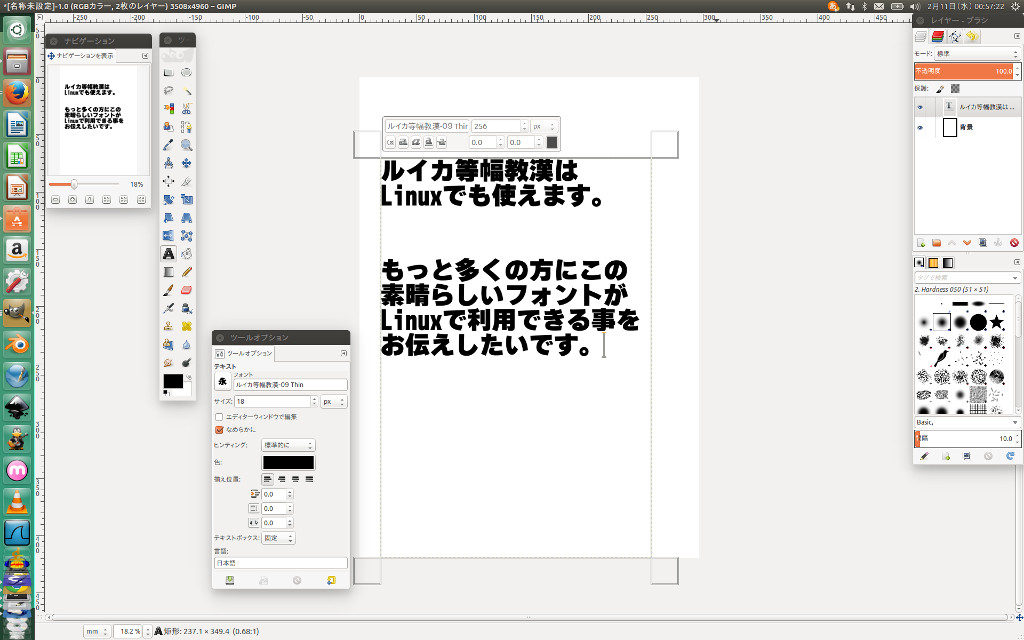
お忙しい中恐縮ですが、お返事いただければ嬉しく思います。
さとうゆたか  2016年5月16日(月) 7:38 [修正]
はるおさん、お問い合わせありがとうございます。
通常の商用利用(印刷物や看板〜)だと思いますので、何の問題もありません。
がんばって販売していただければ…、と思います。
・スヘるお  2016年5月16日(月) 23:24  Mail [修正]
佐藤さま
早々にお答えいただきましてありがとうございます!
それでは有難く利用させて頂き、
がんばって販売していきたいとおもいます。
ありがとうございますm(_ _)m
大学の卒業研究で  ねぎま  2016年2月20日(土) 15:55
こんにちは。
フリーフォントを探しているなかで、こちらの無料配布のフォントのいくつかに心惹かれました。
当方は卒業研究に勤しんでいる大学生なのですが、その卒業研究でフォントに関する調査をしようと思っているのです。
そこで、こちらの無料配布のフォントを研究の材料(ポスターに入れる文字フォント)として利用させていただくことは可能でしょうか?実験内容としては、ポスターに描かれたフォントに関する印象評価、のようなものになります。
私の調べ不足でどこかにこの旨に関する記載がありましたら申し訳ありません。
どうぞよろしくお願いします。
さとうゆたか  2016年2月20日(土) 16:48 [修正]
よくある質問のページに記してあるように、仕事に使っても構わないのですから、研究の材料に使う程度のことに制限をつける気持ちはありません。
どうぞ、利用してください。
ねぎま  2016年2月20日(土) 18:21 [修正]
お早い回答、誠にありがとう御座います。
有り難く利用させていただきます。
タイプラボさんのフォントは冗談抜きで凄い!  くろろ〜ん  2015年10月19日(月) 21:54  Mail
こんばんは!
自分は動画制作をしています。
とは言っても、ずぶの素人で投稿すら至ってませんが(汗
前回に購入した、タイプラボさんのルイカ、わんぱく、ハッピー、アニトなど他にもありますが、とても好きになりました。
特にルイカフォントを動画画面に字幕を付けるだけで、凄まじい位にパワフルな存在感でした。なるほど、だからテレビ番組のテロップでも使われるのかと自分で納得しました。
今現在も、その画面を見るだけで、気持ちを奮い立たせられ『次も頑張るぞ!』と前向きに取り組む様になりました。
文字サンプルでは『ハッキリしていて良い』、『文字が綺麗』と思いましたが、実際に使用して、改めて文字の力というものを実感しました。
以上、長文で駄文になってしまいましたが…。
これからも、フォントをフリーで提供して下さるその善意に、感謝の念を絶やさず、また他のフォント素材屋のサイトさんも同じく、これらのフォントを大切にしてゆきたいと思います。
さとうゆたか  2015年10月20日(火) 14:57 [修正]
熱い感想を投稿していただき、ありがとうございます。
使うフォントによって、モノのイメージって大きく変わりますよね。
そこに気づいてくれてウレシイです。
これからも、フォントをうまく使いこなしてください〜。
WEBフォントとして使用する場合。。  近藤  2015年4月15日(水) 13:50  Mail
いつも使わせて頂いております。ニタラゴルイカはじめルイカは素晴らしいです。
弊社は複数のアーティストサイトをやっていますが、ルイカなどを弊社サーバーにおいて
WEBフォントとして使用する際、どういった費用感、契約になりますでしょうか?
よろしくお願いします。
さとうゆたか  2015年4月15日(水) 14:00 [修正]
よくある質問(Q&A)ページに記してある通り「デコもじ」というWEBフォントサービスを利用してください。
デコもじ↓
↑費用なども詳しく説明されていますので、よろしく〜。
追記…  さとうゆたか  2015年7月28日(火) 21:59 [修正]
フォント組込み契約の対象物件に、WEBサーバを追加しました。
●以下のフォント組込み使用許諾契約書をご覧ください
・総合書体の場合
・かな書体の場合
画像の中にフォントを使用して、その画像を投稿してもいいんですかね  しゅんY12  2015年7月8日(水) 22:53  HP
はじめまして、
先日タイプラボさんの無料版フォント(ニタラゴルイカとキャパニト)をダウンロードさせていただいた者です。
題でも述べましたが、自分のブログやツイッターなどに、『画像のテロップ」の中に、
そのフォントを使いつつ投稿するのは違反行為ですか。それとも普通に使っていいですか。
注意点を読んだんですが、これは「改変」とかにはあたりませんよね?
著作権的な意味でやや心配しておりまして。
心配しすぎ…  さとうゆたか  2015年7月9日(木) 8:35 [修正]
以下のページを読んでいただけたんですよね。
「テロップなどに文字を画像化(アウトライン化含む)して使う分には、上の問いの答えのように自由に使って構いません」と記してあります。
心配しすぎですよ(笑)。
ま、フォントを配布しているのに、いざ使おうとすると制約が多すぎて、実際には使用できそうもないフォントや制約を強いるフォント作者がいるようですが…。
ダウンロードURLの書いたメールが届きません  ももは  2015年7月1日(水) 14:18
つい一月ほど前、無料配布フォントを使用したくメールアドレスを記入したメールをそちらにお送りしたと思うのですが、ダウンロードURLが記入されているはずのメールは届かずメルマガだけが今日届きました。
メアド間違い、というわけではなさそうなのでどうなっているのか…知りたいところです。
また改めて申し込みをすべきなのか、対処方法が分からず困っています。
ちなみに『ルイカ』をDLしたくその時に申し込み手続きをしました。
ご面倒かとは思いますが、回答の方よろしくお願いいたします。
さとうゆたか  2015年7月1日(水) 14:30 [修正]
まずは、無料配布フォントの登録後に表示される以下のページを読んでください。
上記の内容に該当していないのに、メールが届いていない場合は、以下のアドレスまで、直接メールを下さい。
よろしくお願い致します。
ももは  2015年7月1日(水) 16:44 [修正]
先ほど記載されたメールアドレスにメールを送ったのですが、送れませんでした。
もう一度、違うメールアドレスで登録をしなおしてもよろしいでしょうか?
さとうゆたか  2015年7月1日(水) 16:49 [修正]
そうですか…。
違うアドレスでの再登録、構いませんよ。
それでもダメなら、今度は↓こちらにメール下さい。
ももは  2015年7月1日(水) 18:05 [修正]
先ほど、違うアドレスでメールを送らせていただき、無事ダウンロードURLの書かれたメールを手にすることが出来ました。
お騒がせして申し訳ございませんでした。
そしてありがとうございました…!!
文字の加工について(えれがんと)  龍ママ  2015年6月4日(木) 19:23
友人の会社のロゴマークを作る事になり、
無料版の「えれがんと」を利用させていただきました。
Webには昨日より公開されております。
ひらがな4文字なのですが、
えれがんとの最大の特徴である
早速のご回答ありがとうございます。
本当に安心致しました。
これからも宜しくお願い致します。
フォント組込み契約を改訂  さとうゆたか  2015年4月26日(日) 11:26
フォント組込み契約の対象物件に、WEBサーバを追加しました。
・面倒な契約手続きを簡素化してあります
・期間制限や使用量による追加料金はありません
・1ドメインにつき、1フォントの使用許諾です
※ご注意:この商品は、Webフォントサービスを提供するものではありません。
Webフォント用の変換や設置などは、契約者が自己責任で行ってください。
●詳細は、以下のフォント組込み使用許諾契約書をご覧ください
・総合書体の場合
・かな書体の場合